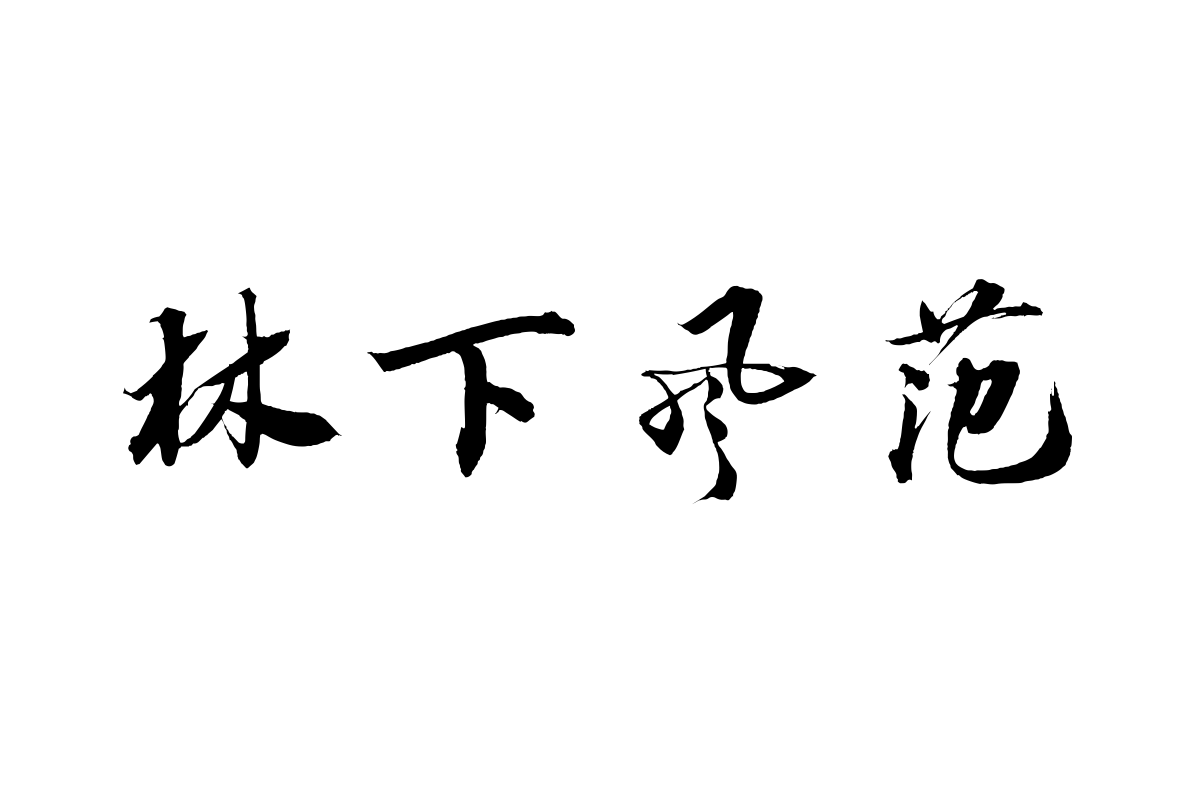
汉仪黄科行书简是一款由汉仪公司推出的免费商用字体,具有独特的书法风格和艺术感。这款字体适用于广告设计、包装设计、书籍封面设计等多种场合,能够为作品增添独特的视觉效果。
汉仪黄科行书简的特点如下:
1. 字形独特:字体线条流畅,结构紧凑,给人一种古朴典雅的感觉。
2. 风格鲜明:字体采用传统的行书风格,笔画粗细变化丰富,既有隶书的庄重,又有楷书的规整,给人以强烈的视觉冲击力。
3. 可读性强:虽然采用了行书风格,但字体结构严谨,笔画清晰,便于阅读和识别。